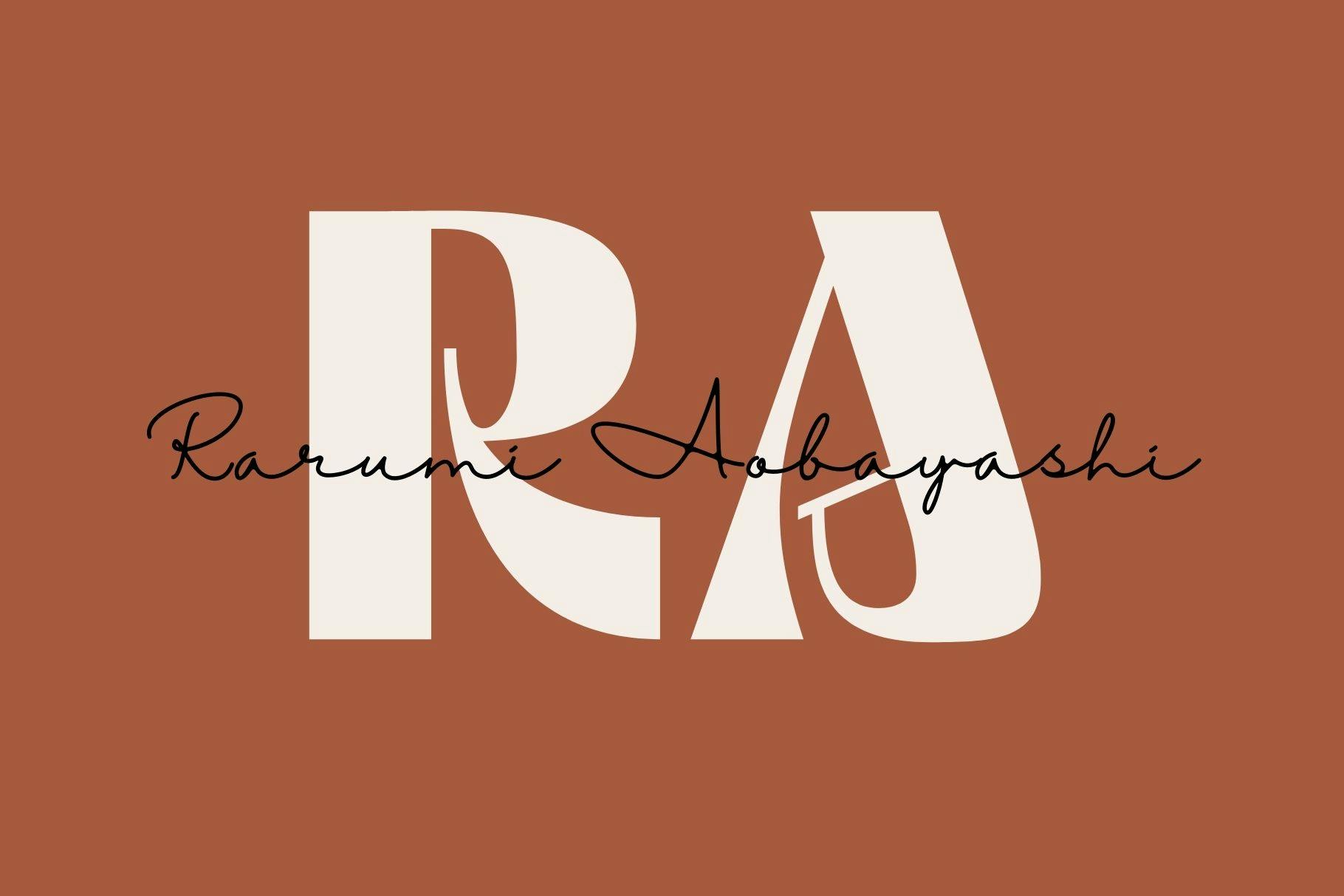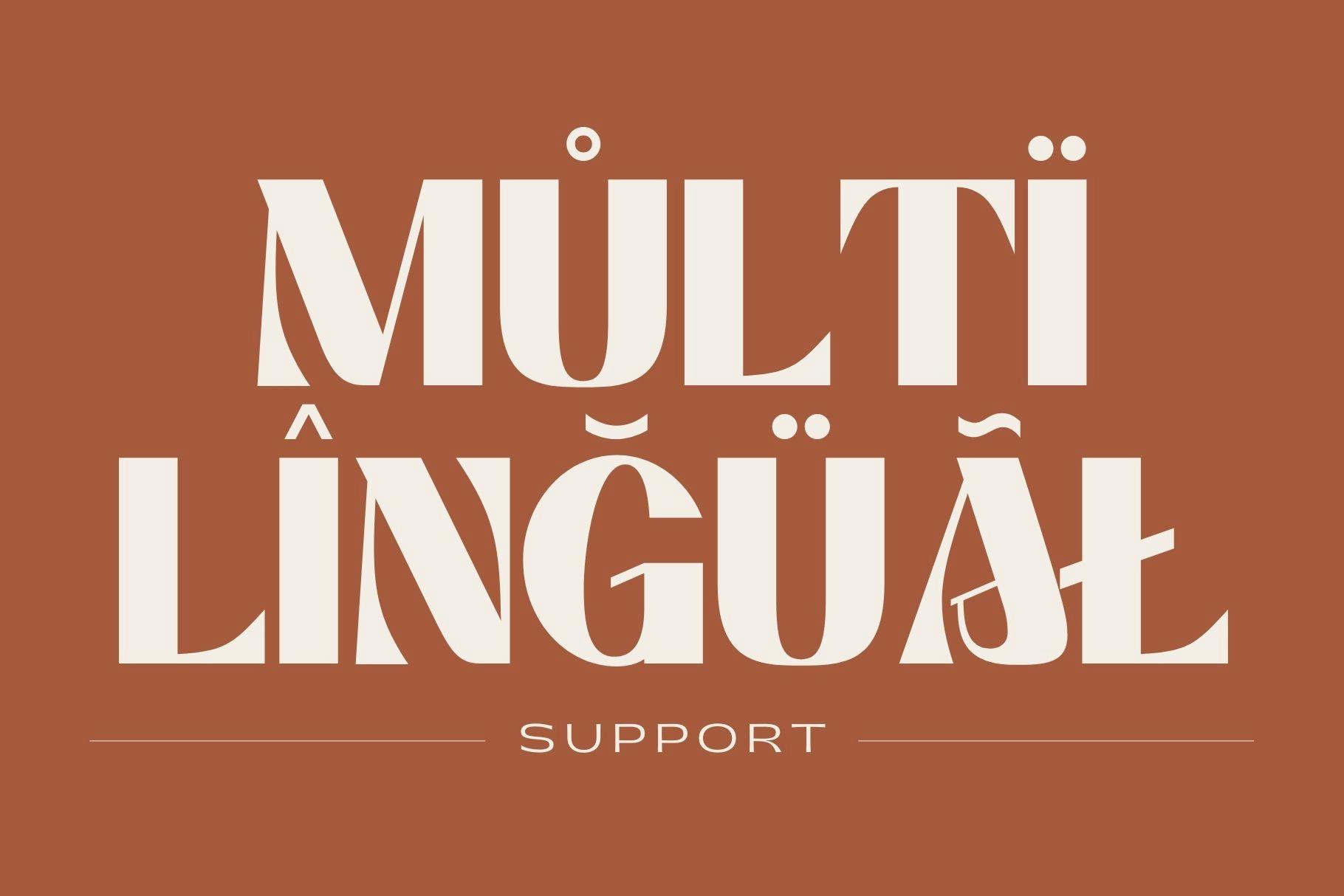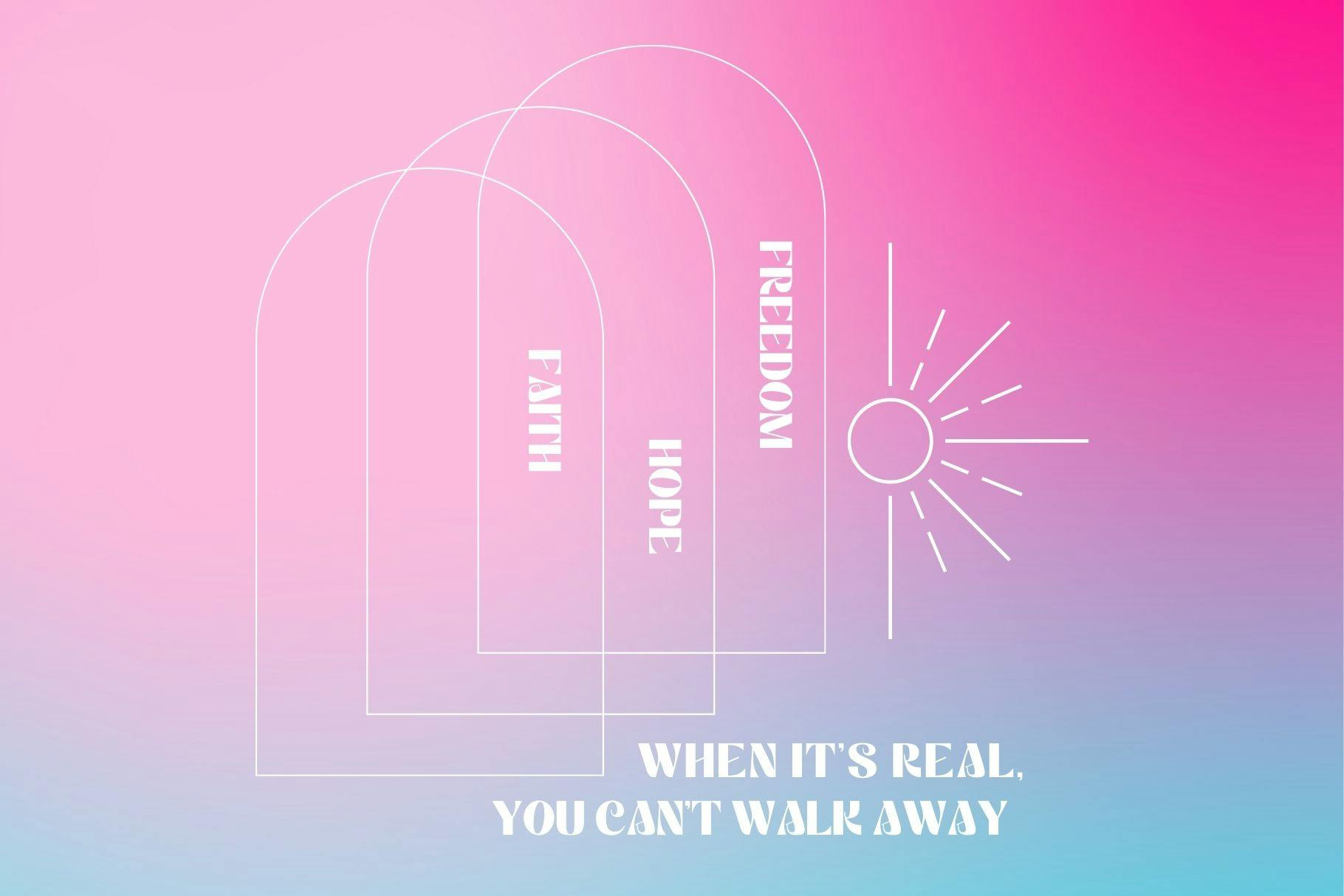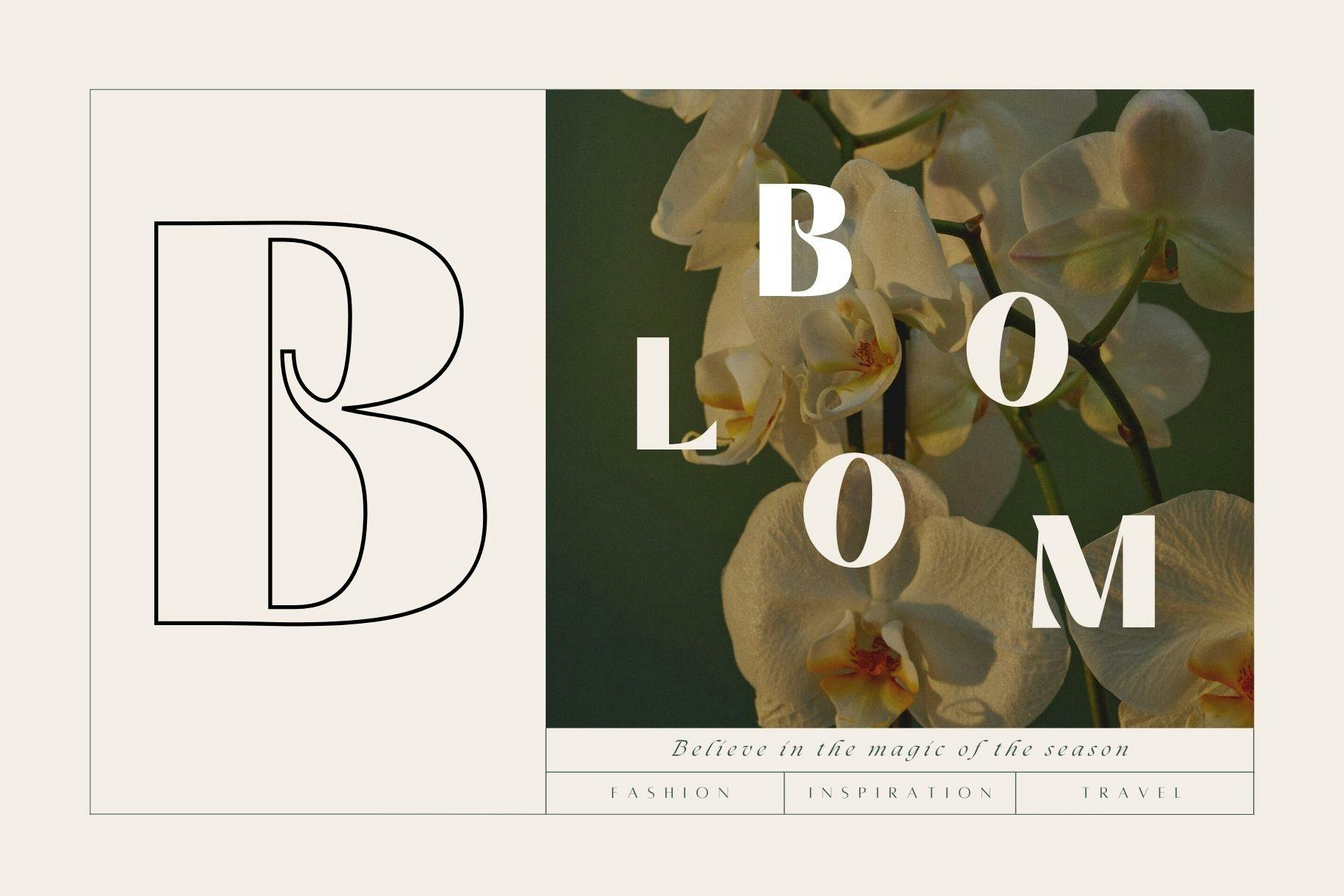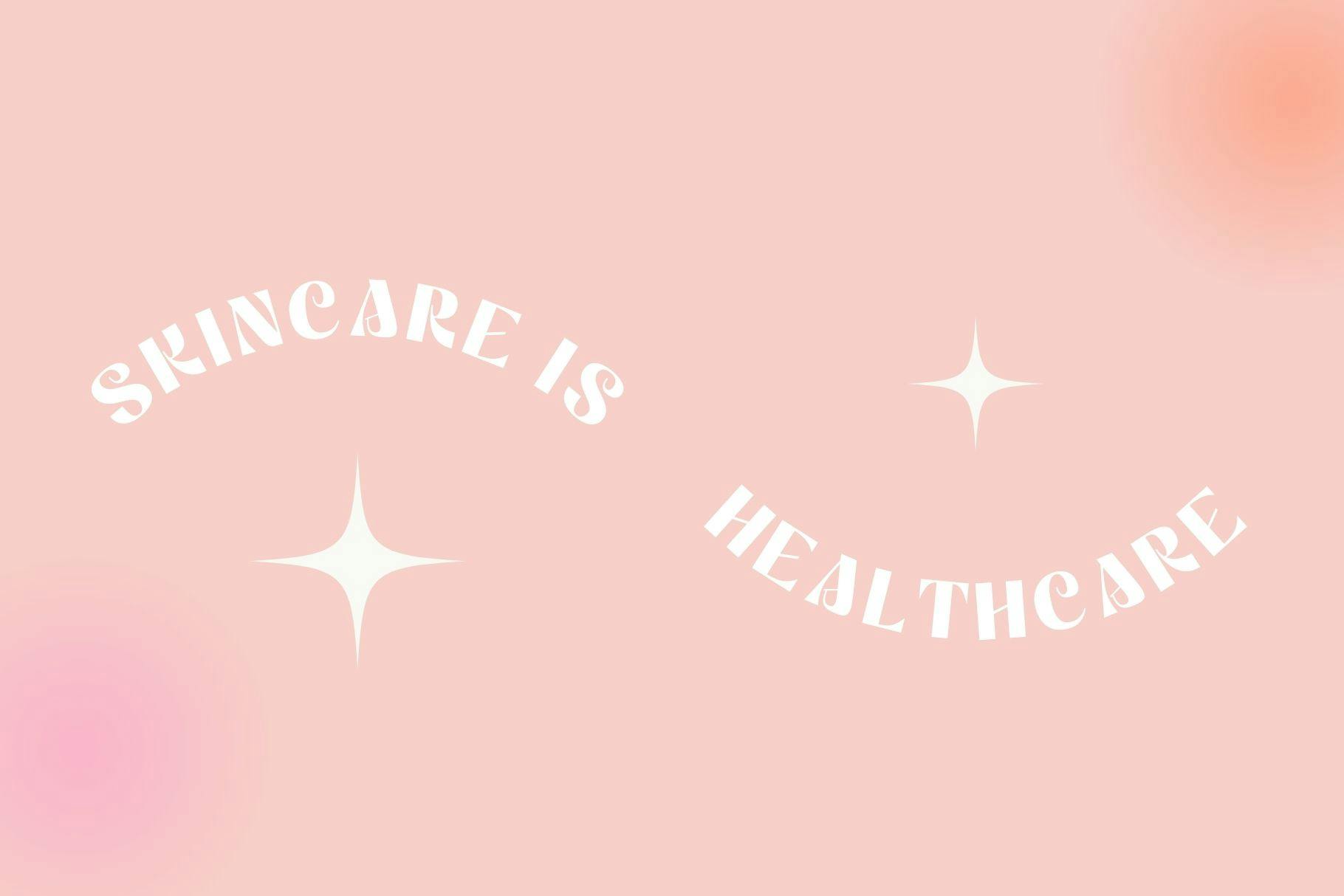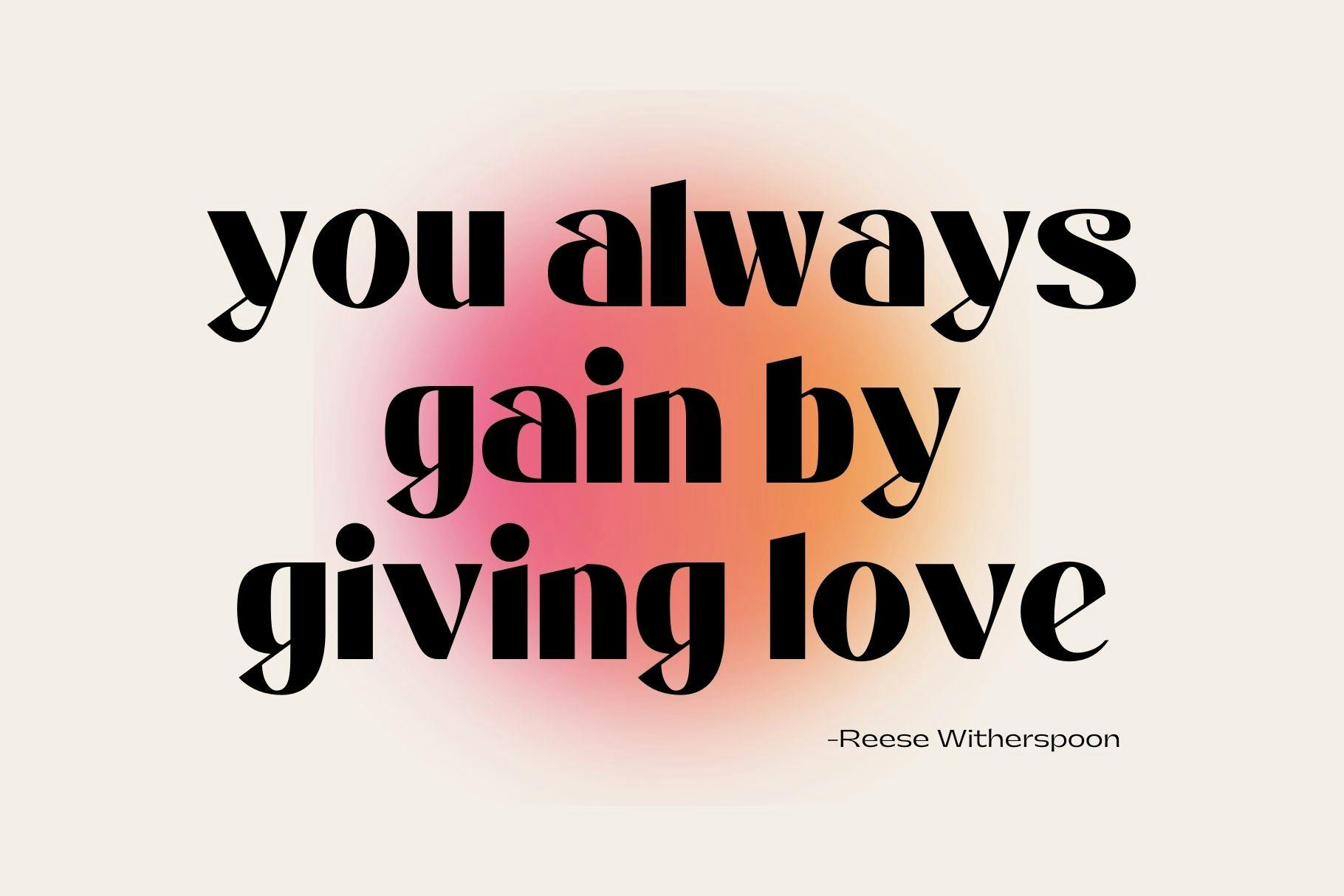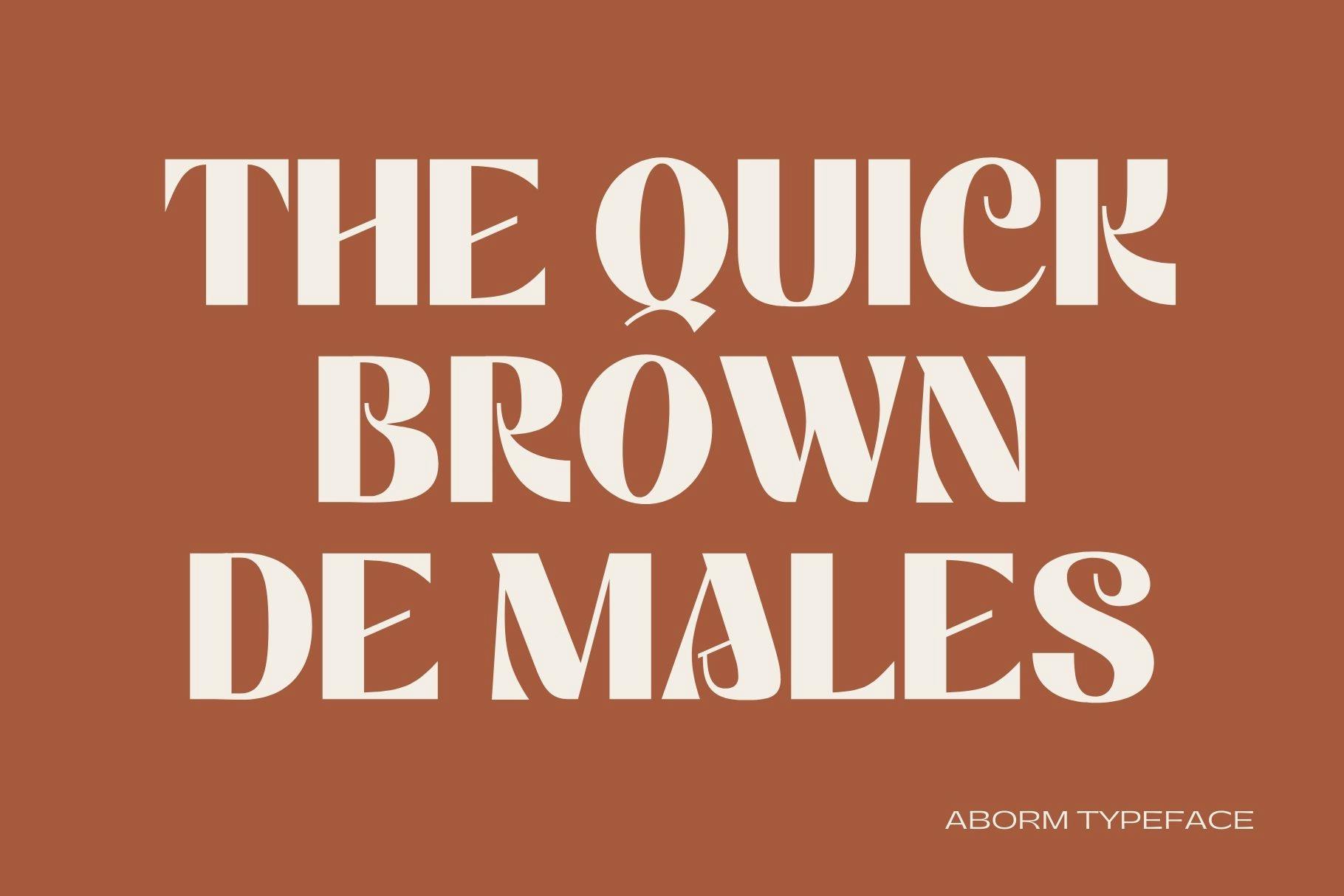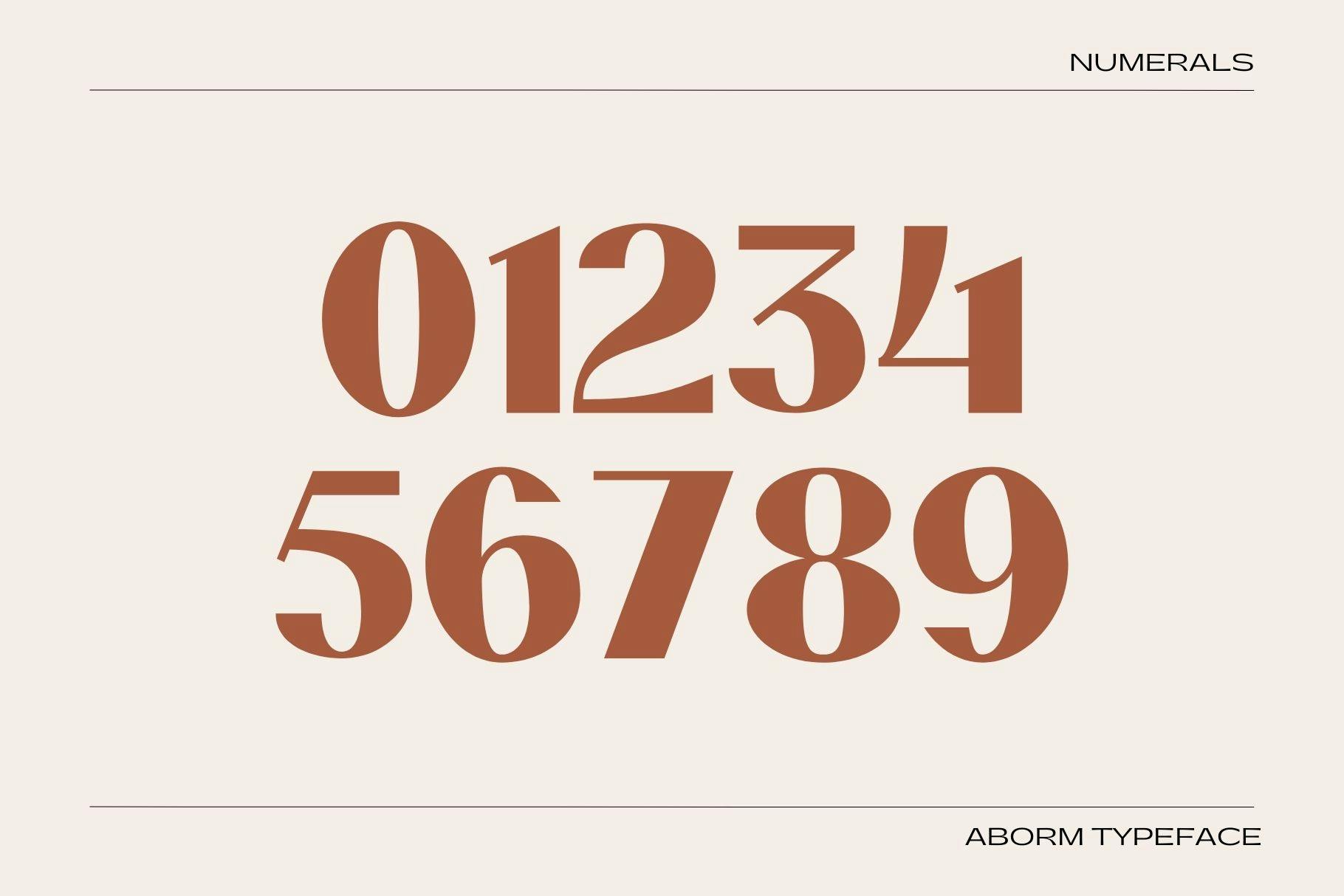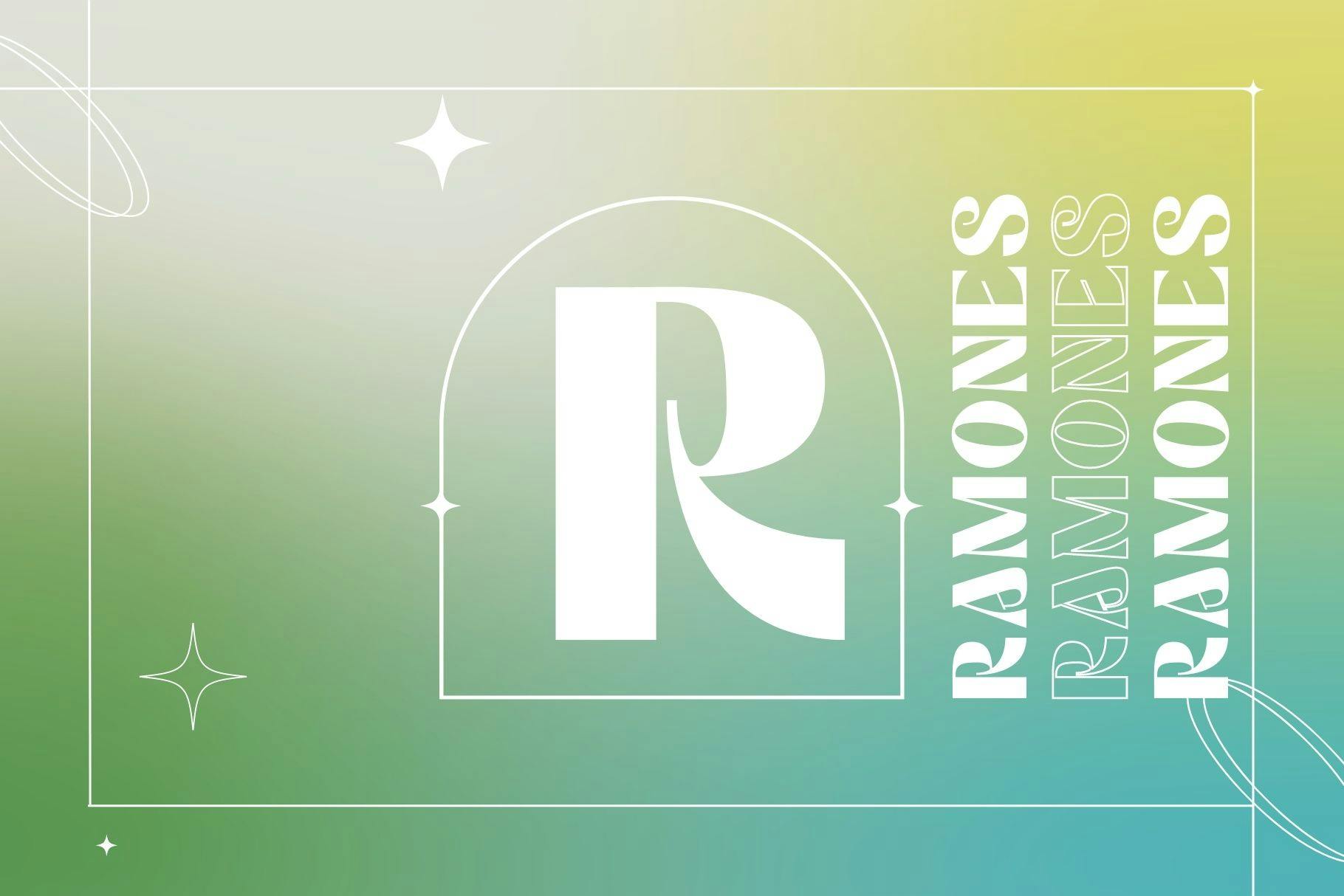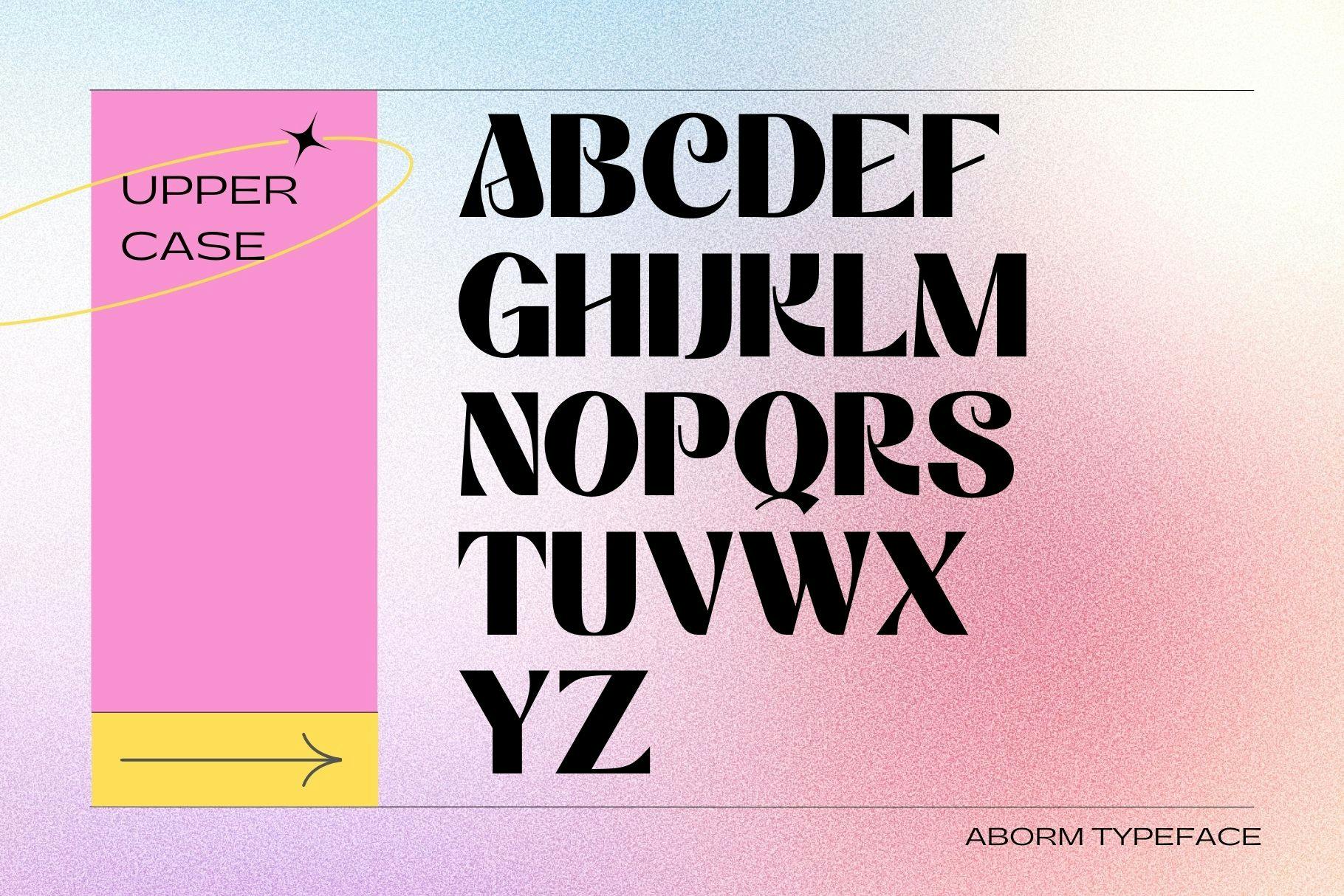
فونت Aborm، همعصر فونتهای Sans serif،
فونت Aborm هارمونی تایپوگرافیکی زیبایی را برای تنوع پروژههای طراحی از جمله لوگو و برندینگ، پستهای رسانههای اجتماعی، تبلیغات و طراحی محصولات ارائه میدهد.